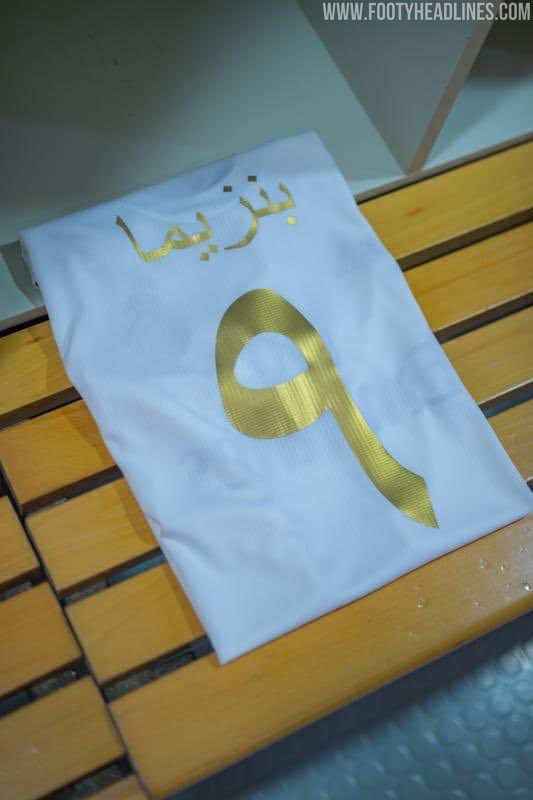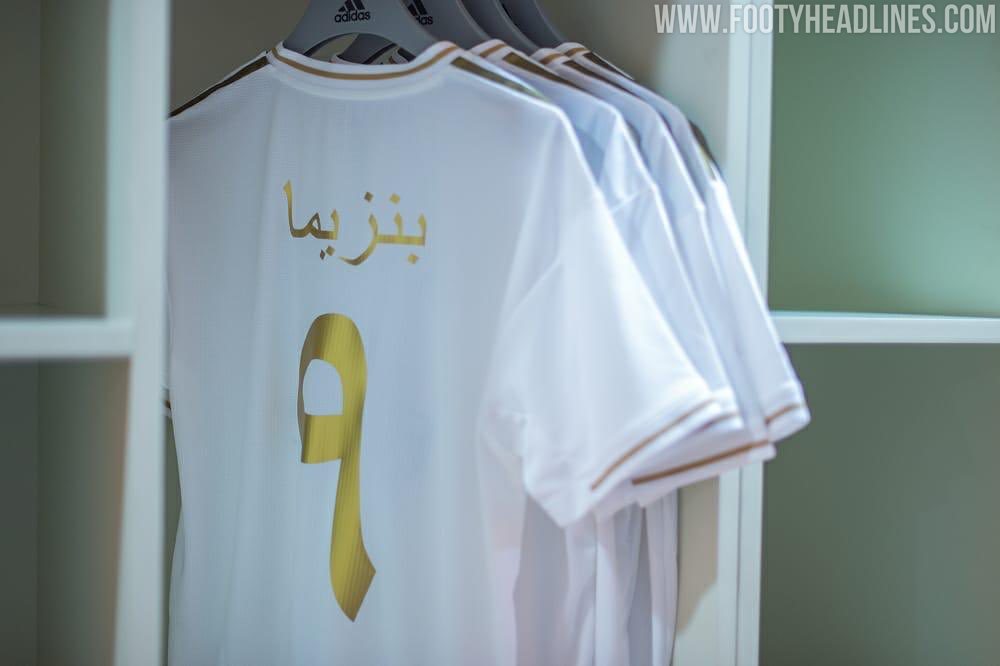
Nicht in Spiel verwendet - Besonderes Real Madrid Spanischer Super Cup 2020 Trikot (Schriftart) enthüllt
Update: Anders als es von Karim Benzemas Tweet angedeutet wurde, trug Real Madrid die reguläre Schriftart im Spanischen Super Cup 2020 Spiel gegen Sevilla am Mittwochabend. Der spanische Fußballverband hat es Real Madrid vermutlich nicht erlaubt, die Schriftart zu tragen.
Real Madrid wird im heutigen Halbfinale des spanischen Super Cup 2019-2020 gegen Sevilla eine spezielle arabische Version seines Adidas-Heimtrikots tragen, wie Karim Benzema angedeutet hat.
Der spanische SuperCup 2019-2020 ist der erste spanische Super Cup, der in einem 4-Team-Format ausgetragen wird. Der Pokal findet vom 8. bis 12. Januar in Saudi-Arabien statt (Halbfinale & Finale, kein Spiel um den dritten Platz).
Real Madrid Spanischer Super Cup 2019-20 Trikot-Schriftart
Die Trikots von Real Madrid für den spanischen Super Cup 2019-2020 weisen eine spezielle arabische Schriftart anstelle der vom Verein verwendeten gewöhnlichen La-Liga-Schriftart auf. Der Stil der Schriftart ist vom traditionellen arabischen Design inspiriert - sie wirkt edler als die fette La Liga-Schriftart.